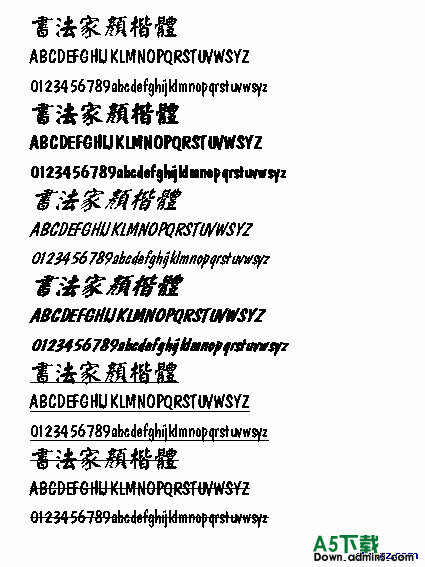
軟件介紹 軟件標簽: 書法家顏楷體 字體 書法家顏楷體繁是很多練習書法的朋友比較喜歡的一種字體,它的每一筆、一頓都給人以力量感,看到讓人心曠神怡,需要的用戶快到綠色資源網(wǎng)下載體驗吧!書法家顏楷體繁介紹這款書法家顏楷體字體字形牽絲勁挺,同樣濃同樣纖,適用于繪畫設計、藝術創(chuàng)作等領域。本文為整理了對于字體的安裝方法。書法家顏楷體(繁)字體安裝方法:windows下找到"控制面板 - 外觀 - 字體",粘貼書法家顏楷體(繁)字體文件即可; mac下找到"系統(tǒng)-資源庫-fonts",粘貼書法家顏楷體(繁)字體文件即可,亦可用字體冊添加。 軟件截圖 上一張下一張(1 / 1) 安裝詳細截圖 猜你喜歡 顏體字體 書法字體 顏體字體 顏體是一款極具古樸厚重韻味的字體,這里匯集了各具特色的顏體字體,每款字體都有著顏體豐腴雄渾、骨力遒勁的魅力,因此顏體也深受廣大書法家的喜愛,下面有綠色資源網(wǎng)小編為大家提供顏體字體下載大全,感興趣的朋友歡迎來綠色資源網(wǎng)下載體驗! 查看更多>> 經(jīng)典簡顏體字體 2.44M/中文/1.2/下載 tianshi-yanti字體 2.92M/中文/5.0/下載 全真顏體簡體字體 4.88M/中文/2.5/下載 fashionfont052 by字體 2.44M/中文/2.0/下載 刻石錄顏體字體 8.53M/中文/5.7/下載 顏體字體下載大全 52.01M/中文/1.6/ttf下載 書法字體 書法字體有哪些?主要包括了硬筆書法字體、英文書法字體和毛筆書法字體三大類,綠色資源網(wǎng)提供了多款好看的常用各種書法字體文件打包下載,如:李旭科書法字體、啟功書法字體等,趕快下載體驗吧! 查看更多>> 蔡云漢隸書書法字體ttf 2.61M/中文/10.0/下載 黃庭堅字體 2.39M/中文/6.6/下載 李旭科書法v1.4-中 3.59M/中文/7.7/下載 金梅書法豆豆 2.03M/中文/10.0/下載 金梅新海報書法 2.24M/中文/10.0/下載 劉夢吟書法行楷字體 3.66M/中文/10.0/下載 其他版本下載 標題 大小 更新日期 下載 下載地址 電腦版 書法家顏楷體(繁) 點擊報錯 軟件無法下載或下載后無法使用,請點擊報錯,謝謝! 關閉報錯反饋 請描述您所遇到的錯誤,我們將盡快予以修正,謝謝! *必填項,請輸入內容 本類最新 datm9 datx2 datk8 dath9 datk6 書法家特圓體字體 相關文章 Photoshop字體安裝使用方法和技巧 如何解決“無法新增字體”問題 Win 7系統(tǒng)安裝字體方法 網(wǎng)頁字體大小設置方法 怎么改網(wǎng)頁字體大小 在Linux系統(tǒng)中安裝字體的幾種方法 windows7字體顯示問題:打開某些程序的時候顯示的是亂碼 用戶評論 熱門評論 最新評論 發(fā)表評論 查看所有評論(0) 昵稱: 請不要評論無意義或臟話,我們所有評論會有人工審核. 字數(shù): 0/500 (您的評論需要經(jīng)過審核才能顯示)